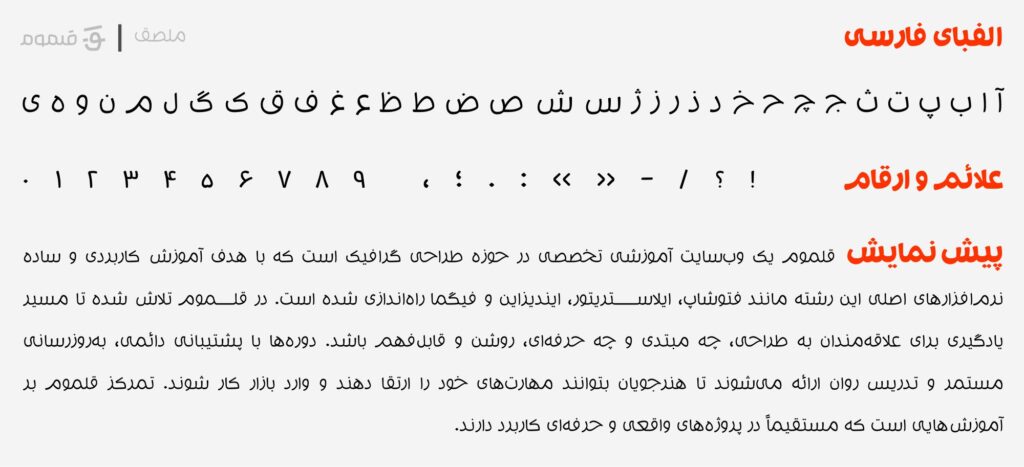
فونت ملصق یک تایپفیس عربی زیبا و پرکاربرد است که علاوه بر حروف عربی، از حروف فارسی نیز بهطور کامل پشتیبانی میکند. این فونت در سه وزن مختلف ارائه شده و بهصورت رایگان در دسترس کاربران قرار دارد.
ملصق به دلیل طراحی ساده و خوانا، گزینهای ایدهآل برای متنهای طولانی، رابطهای کاربری دیجیتال و حتی پروژههای چاپی است. همچنین بهخاطر پشتیبانی همزمان از زبان فارسی و عربی، برای طراحیهای چندزبانه بسیار مناسب خواهد بود.